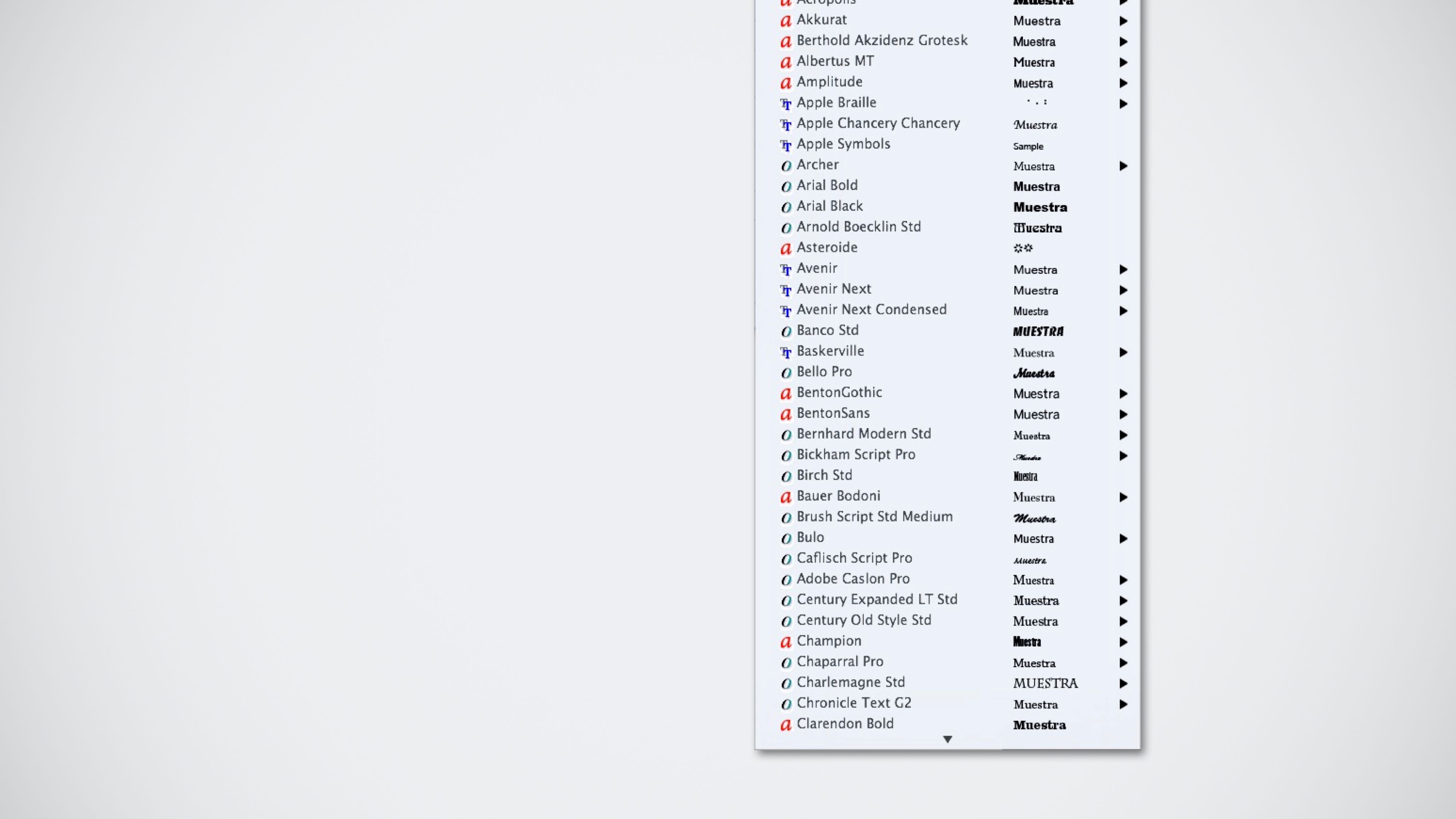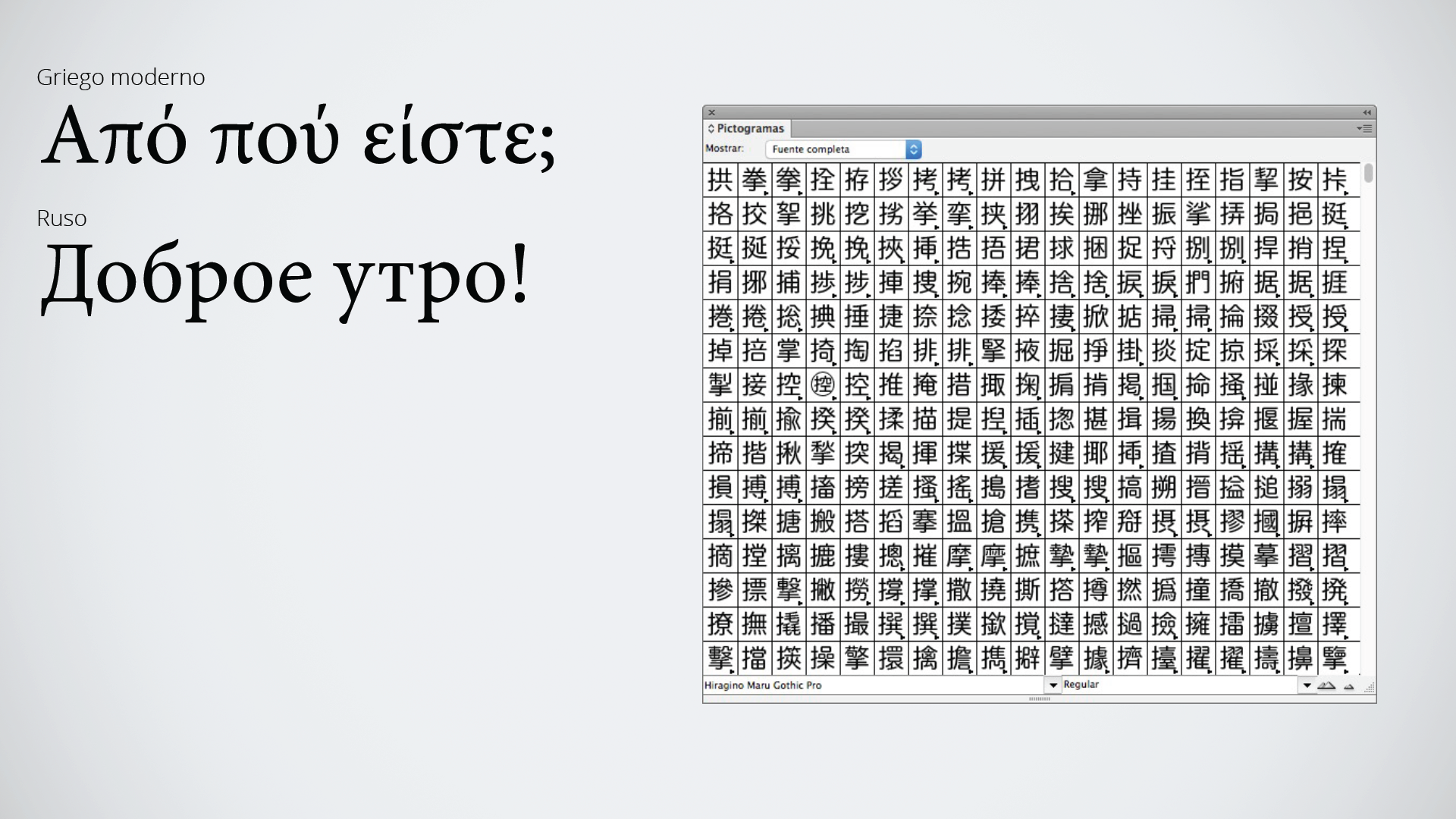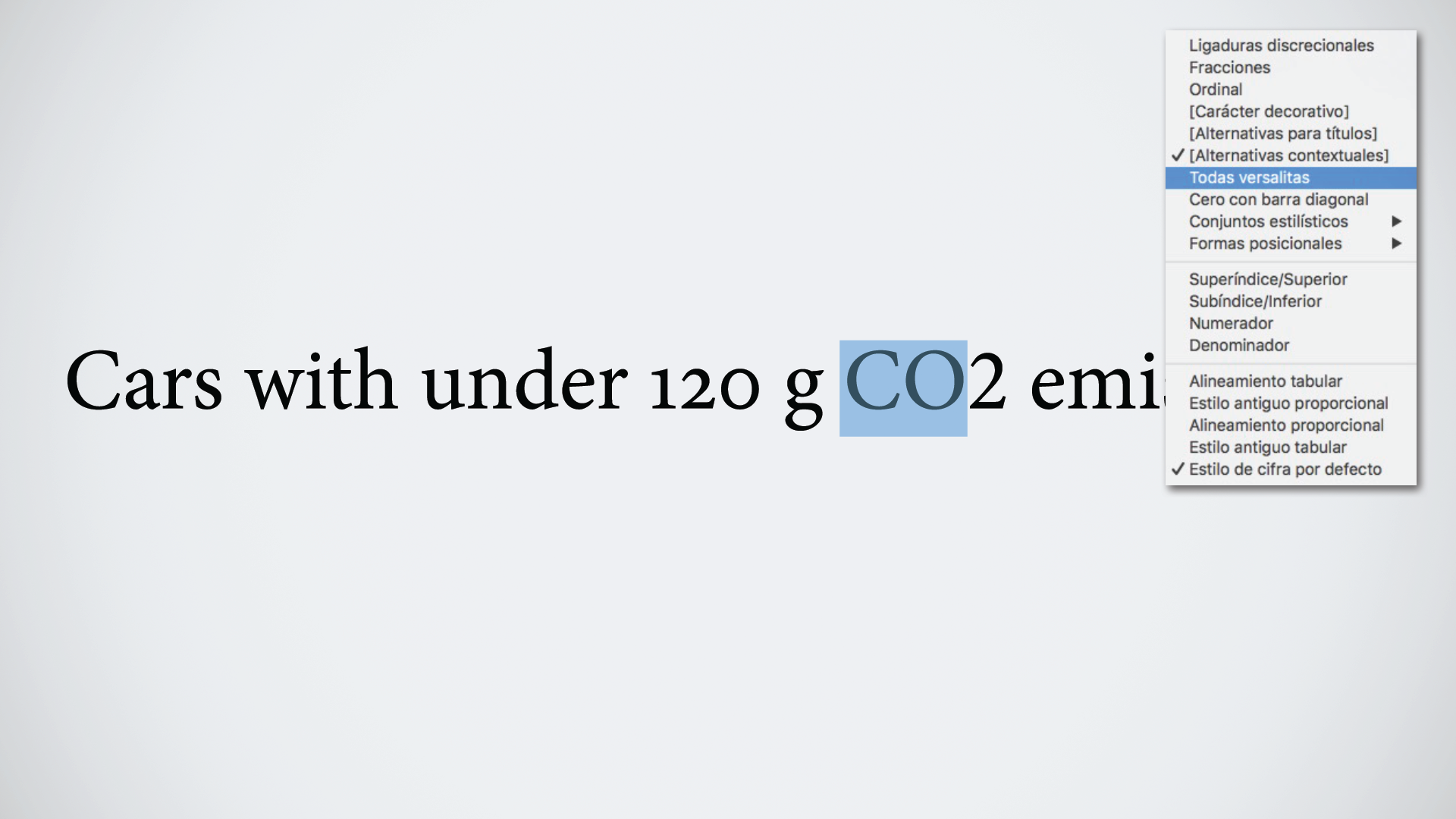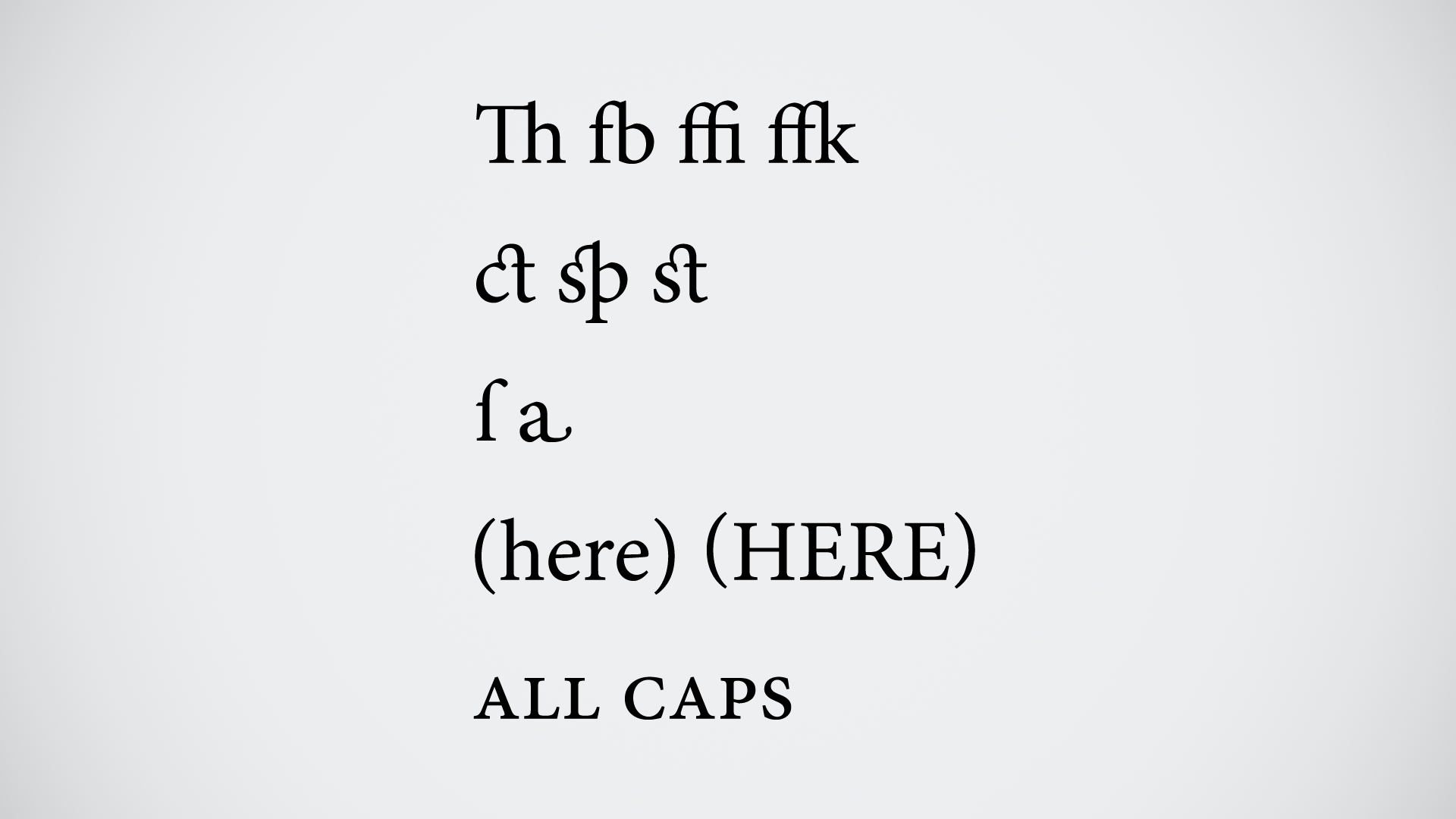
Tutorial Tipografía: las fuentes OpenType
Descubre con Enric Jardí las ventajas de utilizar las fuentes OpenType en tus proyectos de diseño editorial
OpenType es un formato tipográfico único y escalable, capaz de ofrecer una completa gama de tipografías, y que además es capaz de adaptarse a los principales sistemas operativos (Windows, Mac y Unix). Enric Jardí, diseñador gráfico especializado en diseño editorial y tipográfico, nos descubre todos sus secretos a la hora de sacar el máximo provecho a las fuentes OpenType.
1. Compatibilidad entre sistemas operativos
Antes de aparecer las tipografías OpenType, cuando pasábamos un proyecto de un sistema operativo a otro, había ciertas fuentes que, al estar disponibles en ambos sistemas, podíamos volver a utilizar sin problema. Era la misma fuente, sí, pero no exactamente el mismo archivo, y eso podía provocar problemas. Esto cambió con las tipografías OpenType.
Estas tipografías se pueden utilizar tanto en un sistema operativo Mac como en Windows o Unix, lo que permite compartir la fuente cuando trabajamos, por ejemplo, en Illustrator o InDesign y queremos cambiar de sistema operativo, conservando tanto las fuentes utilizadas como los archivos.
2. Acceso a hasta 64.000 caracteres
Las tipografías OpenType están preparadas para alojar hasta 64.000 caracteres; esto no quiere decir necesariamente que cada una de ellas contenga ese número de caracteres, sino que están preparadas para contenerlos en caso de que sea necesario.
Esto permite acceder a escrituras similares a la nuestra, como la griega o la cirílica, y a otras como la china, que requieren una cantidad de caracteres mucho mayor. Esta característica del OpenType permite visualizar sin problemas, por ejemplo, las webs escritas en chino o japonés.
3. Acceder a grupos estilísticos
En algunas fuentes OpenType podemos activar partes de la escritura para que caracteres específicos se comporten de la forma que nos interese. Por ejemplo, podemos transformar a versalitas un determinado grupo de caracteres, dándoles un estilo particular:
Y también permite que los números trabajen de manera especial, por ejemplo, convirtiéndolos a superíndices:
Esto se puede configurar en las opciones de estilo de carácter o estilo de párrafo, para no tener que cambiar los caracteres cada vez que lo necesitemos.
4. Acceder a caracteres especiales
OpenType permite también acceder a otros caracteres especiales, como las ligaduras. Con ellas, conseguimos efectos, en ocasiones más ornamentales y en otras simplemente prácticos, en las uniones entre distintas letras.
Aunque la mayoría de fuentes cuentan con algunas ligaduras, son las fuentes "pro" (como 'Adobe Garamond Pro', por ejemplo) las que tienen opciones para generar lo que llamamos ligaduras discrecionales: grupos de letras ligados entre sí con un carácter más ornamental; o formas de letras que, al estar posicionadas al final de una palabra, tienen una forma distinta; o paréntesis que se adaptan a las mayúsculas o minúsculas.